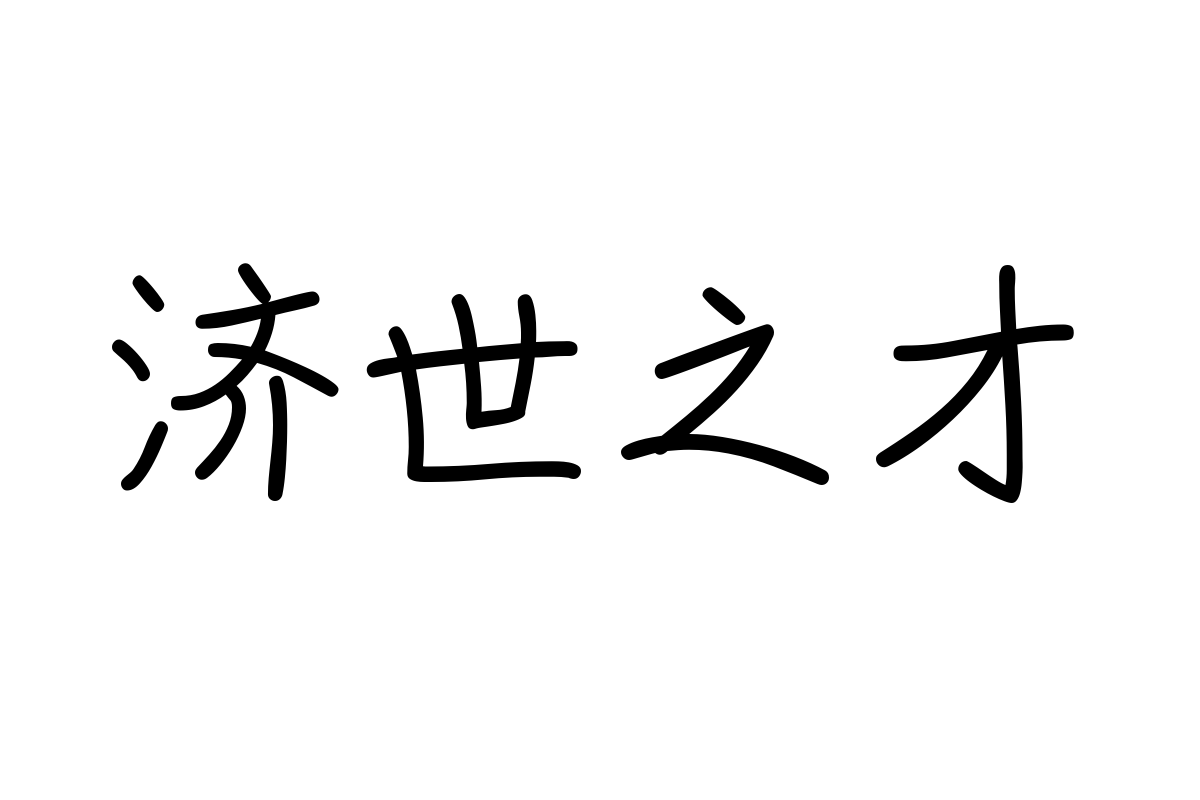
字体管家天真是一款免费、开源的中文字体,由字体管家团队开发。这款字体具有独特的设计风格,适合用于各种设计场景,如网页设计、平面设计等。天真字体采用简洁的线条和形状,给人一种轻松、自然的感觉。同时,字体的笔画粗细适中,既不会过于粗犷,也不会过于细腻,适合用于需要突出文字内容的设计作品。此外,天真字体还支持多种字重和字号设置,可以根据不同的设计需求进行调整。总的来说,字体管家天真是一款值得推荐的免费中文字体。